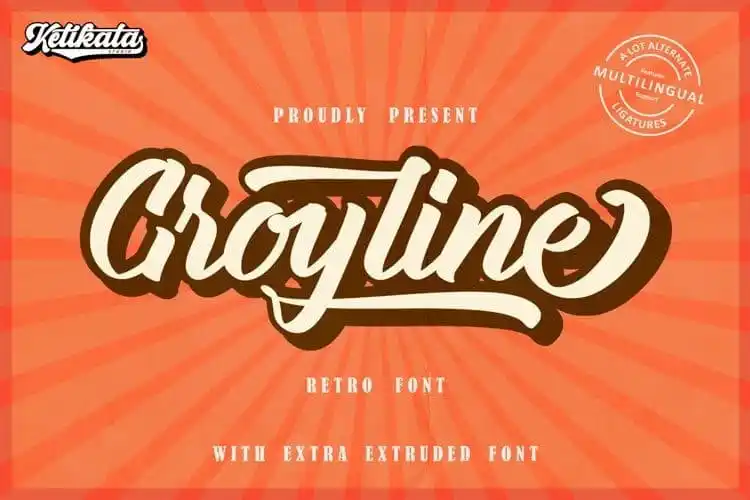
Groyline Script Font – Download Grátis
A Groyline Script Font é uma elegante fonte semifinalizada desenvolvida pelo Designer 99designs, proveniente da Ketikata Studio. Esta fonte é ideal para quem busca agregar um toque único e atraente aos seus trabalhos de design. Ela não apenas oferece uma aparência limpa e agradável ao olhar, mas também traz muitas alternativas estilísticas e “swashes” que permitem personalizá-la conforme necessário, criando designs únicos e exclusivos. A Groyline Script Font foi cuidadosamente construída a partir de letra à mão, garantindo uma identidade visual única. Seja para criar logotipos, gráficos em cartão ou qualquer outro projeto de design que exija um toque especial e autêntico, esta fonte semifinalizada é perfeita. Sua aparência sofisticada e o leque de alternativas estilísticas oferecidas permitem a criação de designs personalizados com facilidade. Seja você um designer profissional ou iniciante em design gráfico, a Groyline Script Font certamente se adequará aos seus projetos, dando uma nova dimensão a eles.